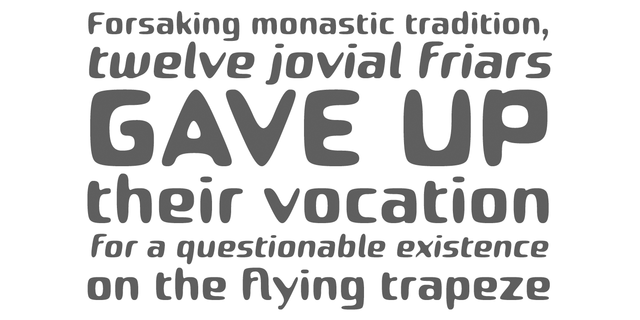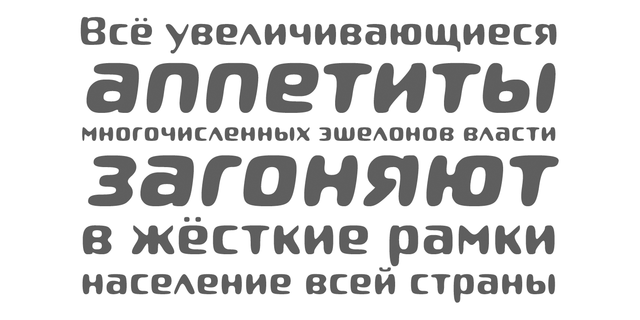
Шрифт Робу дружелюбен и обаятелен и обладает хорошей разборчивостью. Шрифт включает четыре начертаня с многоязычным комплектом символов. Робу отлично подходит для рекламы, упаковки подуктов питания и различных товаров для детей. Разработан Сергеем Ткаченко в 2014 году.
Функции начертания Roboo 4F Bold ItalicПрименение в макете:
Ассоциации c начертанием Roboo 4F Bold ItalicКачества и характер:
добродушный, дружелюбный, мягкий, сильный, приветливый, доверительный, добрый, позитивный, милый, молодежный, оригинальный, плавленый, гладкий, статичный, веселый, смешной, озорной, свежий, спелый, вкусный, простодушный, детский, мультяшный, праздничный, надувной, сочный, игривый, мотивирующий, домашний, резиновый
завтрак, детская книжка, игрушка, еда, молоко, лагерь, фломастеры, пластилин, юмор, анимация, праздник, соус, фаст фуд, закуска, мороженное, кондитерская, сладости, выпечка, булочки, булочная, сметана, зоопарк, жвачка, игра, пицца, зоомагазин, животные, отдых, мягкая игрушка, мультфильм, украшение, шоу, телевидение, смузи, кетчуп, чипсы, наклейка, стикер Стилистика: